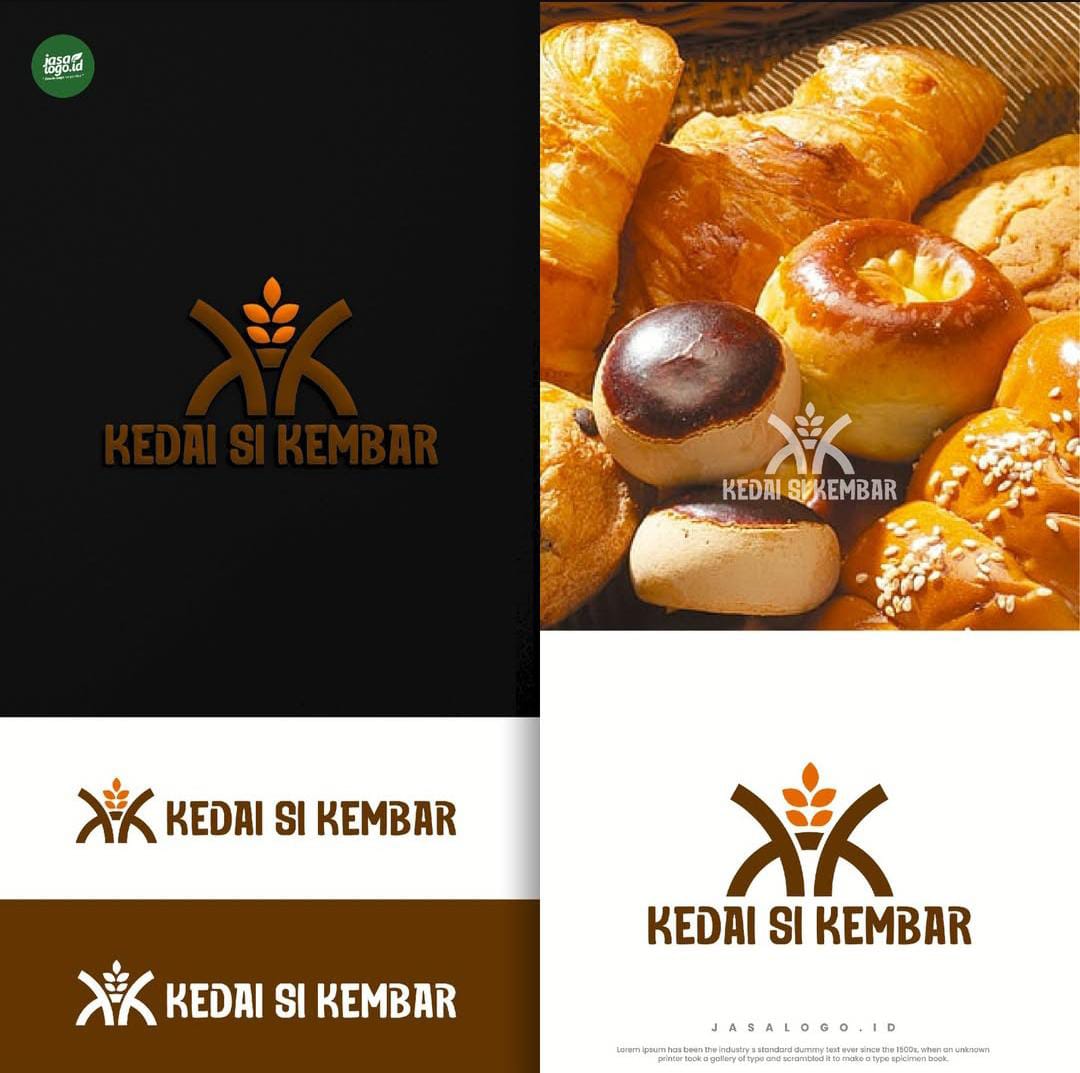
Jenis font yang sederhana seperti font serif dan sans serif memang populer digunakan untuk desain logo. Hal ini karena memiliki bentuk sederhana dan mudah dibaca, tetapi bisa membuat logo akan kurang unik. Gaya tipografi font display yang sederhana dapat digunakan sebagai alternatif agar desain logo lebih menarik dan unik.
Dibandingkan font lainnya, jenis font display memiliki gaya huruf yang lebih bebas sehingga tipografi saja bisa menciptakan logo yang unik. Memilih desain huruf yang unik, bisa menjadi salah satu cara membuat logo lebih menarik dan tampil beda.
FONT DISPLAY
Gaya huruf dalam font display cenderung bebas, tidak beraturan dan terkadang cukup unik. Beberapa diantaranya bisa digunakan sebagai desain logo yang unik tanpa tambahan dekorasi atau ikon. Namun dalam desain logo gaya hurufnya tetapi harus mudah dibaca agar logo mudah dikenali.
Style font display bisa menarik perhatian audiens pada logo karena tampil beda dan unik, untuk itu pilih gaya font yang tepat. Seringkali pada desain logo banyak menggunakan style font display yang sederhana, seperti tulisan tangan, memiliki gaya huruf bulat dan tidak sejajar semua hurufnya. Contohnya pada font logo burger King dan pampers yang menggunakan font display sederhana.
KESAN YANG DICIPTAKAN
Gaya huruf pada font display seringkali memiliki ketebalan, ketinggian, tata letak yang tidak sama sehingga tampil unik meski memiliki huruf bersih. Font display sendiri memiliki banyak variasi gaya huruf yang bisa menciptakan kesan berbeda. Namun biasanya font display yang unik dan tidak sama ini akan menciptakan kesan unik dan menyenangkan.
Casual
Banyak gaya tipografi yang digunakan dalam desain logo akan memilih font style sederhana dan santai. Font display yang bulat dan bentuk huruf yang tidak sama akan menciptakan kesan casual.
Tipografi font display bisa menciptakan gaya tipografi yang santai dan sederhana. Terutama juga pada gaya huruf yang bersih dan bulat, font akan tampil lebih ramah. Gaya huruf casual ini akan relevan untuk desain brand makanan dan minuman.
Unik
Gaya huruf font display dalam desain logo akan menciptakan desain yang unik dan menarik. Hal ini karena bentuk hurufnya yang tidak rapi, tidak sejajar dan tidak sama, bahkan untuk gaya huruf sederhana setiap hurufnya tampil beda.
Beberapa diantaranya ada yang memiliki bentuk unik seperti geometris atau memiliki dekorasi. Gaya huruf yang unik ini dipilih untuk menciptakan desain logo yang tampil beda meski hanya menggunakan font saja.
Personal
Terkadang tipografi font display yang digunakan dalam desain memiliki gaya huruf seperti tulisan tangan. Hal ini akan terlihat dari bentuk huruf yang tidak konsisten seperti tulisan tangan.
Gaya ini akan menciptakan tipografi berkesan personal. Gaya huruf yang berkesan personal ini akan menciptakan desain logo yang menarik. Hal ini karena logo akan terkesan berbeda dan eksklusif karena seperti tulisan tangan khusus.
Menyenangkan
Font display yang memiliki sudut melengkung dan gaya huruf bulat seringkali akan berkesan menyenangkan dan ramah. Gaya huruf yang bulat cocok digunakan untuk desain logo makanan atau minuman. Namun font display yang bulat juga bisa digunakan untuk berbagai kebutuhan lain untuk merepresentasikan kesan menyenangkan.
Tipografi font display yang bulat pada desain logo, juga seringkali memiliki ukuran yang tidak konsisten. Untuk itu tipografi menciptakan kesan menyenangkan dan ceria.
TIPOGRAFI FONT DISPLAY DALAM DESAIN LOGO
Penggunaan tipografi font display pada desain logo bisa menciptakan logo yang sederhana namun tetap unik. Bentuk font yang tidak konsisten justru akan menciptakan logo yang lebih unik. Pilih style font display sesuai karakter yang ingin diciptakan dan dapat menciptakan logo yang unik
Logo Minuman
Pada desain logo minuman, tipografi display akan menciptakan kesan yang menyenangkan dan kasual. Gaya huruf pada logo terlihat memiliki tebal, tidak konsisten dan bentuk huruf sederhana yang mudah dibaca. Kesan ramah pada tipografi terlihat harmonis dengan ikon logo line art tersebut.
Gaya tipografi display untuk logo minuman dapat menciptakan kesan menyenangkan dan ramah. Font display bisa menciptakan logo minuman yang ramah dan terasa dekat dengan konsumen. Tidak hanya itu font tersebut mudah untuk dibaca karena memiliki huruf yang bersih.
Logo Kopi
Brand kopi tersebut juga memiliki style tipografi yang sederhana tetapi unik karena gaya hurufnya tidak konsisten. Bentuk huruf yang tidak konsisten tersebut tampak ramah dan menyenangkan. Font display yang tebal dan bulat tersebut mudah dibaca dan konsisten untuk tampil jelas.
Font tebal yang digunakan harmonis dengan bentuk ikon kombinasi mata dan biji kopi. Warna hitam membuat tipografi semakin jelas dibaca dan berkesan estetik. Bentuk huruf bulat dan tidak sejajar tersebut menciptakan kesan brand kopi yang menyenangkan.
Penggunaan gaya tipografi unik dan sederhana dalam desain logo bisa menjadi identitas yang unik tetapi juga mudah dibaca. Gaya tipografi font display yang sederhana, bebas dan tidak konsisten akan tampil unik dalam desain logo. Font display seringkali memiliki gaya huruf bulat, sederhana, tebal dan gaya huruf bebas seperti tulisan tangan. Gaya huruf akan mencerminkan brand yang ramah dan menyenangkan.